Строчная «ч» в рукописном шрифте: как согласовать дугу и правую стойку
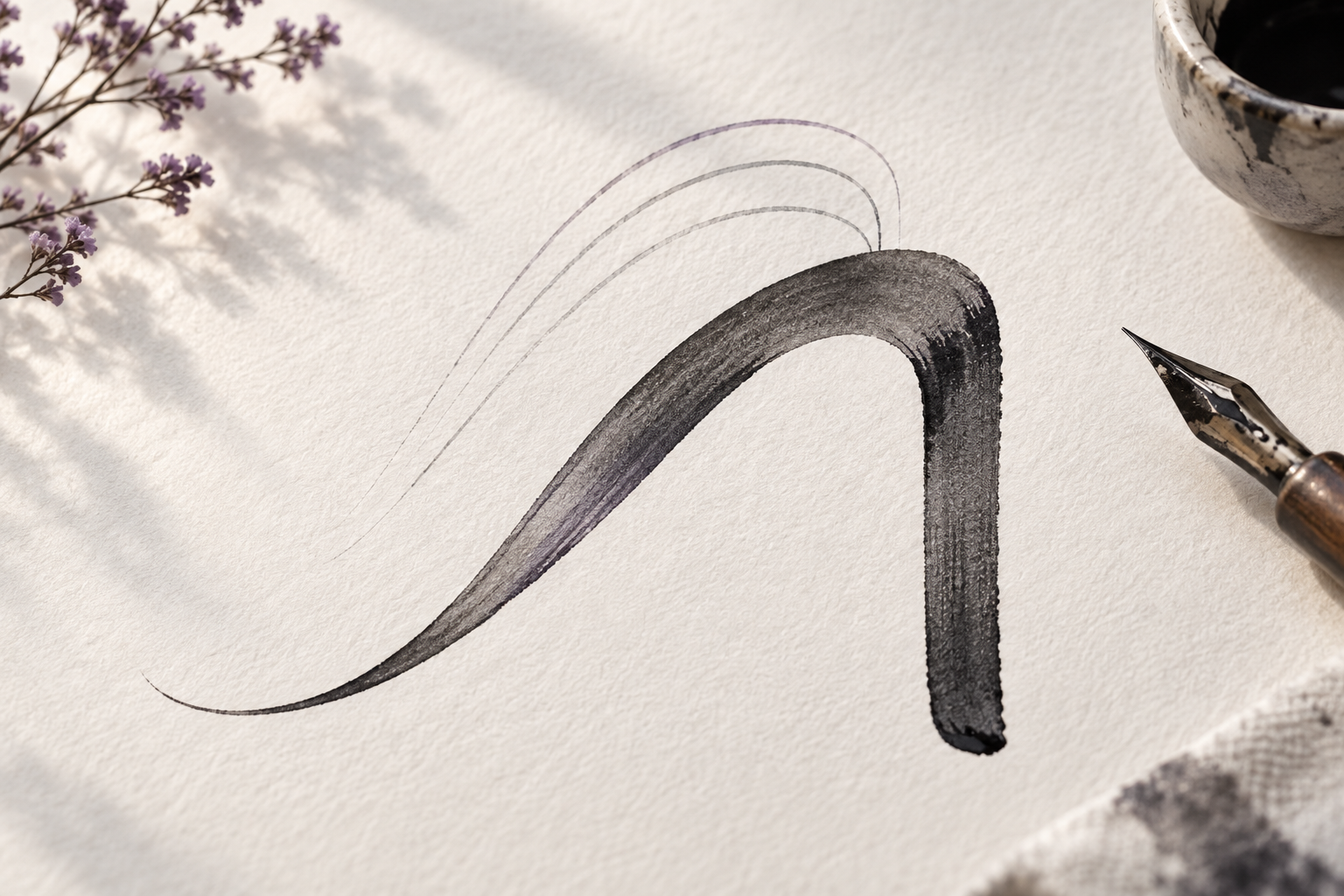
В строчной «ч» дуга должна перейти в правую стойку так, чтобы знак выглядел продолжением общего почерка, а не отдельной геометрической конструкцией. Начните с каркаса и точек перехода, затем настройте ширину чаши, наклон стойки и толщину на повороте. Такой порядок помогает избежать жёсткого угла, провисающей дуги и случайно тяжёлого правого края.
Что именно решает рисунок строчной «ч»
У этой буквы небольшой набор деталей, поэтому каждая заметна: левая сторона поднимается в дугу, дуга возвращается вниз и заканчивается правой стойкой. В рукописном начертании траектория зависит от того, как задуман жест: дуга может быть широкой и мягкой или компактной и энергичной, а стойка — почти вертикальной или слегка наклонённой. Важно, чтобы переход между ними был понятен и повторял логику остальных букв.
«Ч» часто кажется простой, пока её не ставят рядом с «и», «ш», «щ» и «п». Тогда обнаруживается, что чрезмерно округлая дуга сбивает темп, а слишком прямой верх превращает знак в чужую деталь. Стойка может начинаться слишком резко, перетягивать на себя взгляд или уходить в сторону. Эти эффекты не исправляются одинаковым наклоном всех штрихов: сначала нужно договориться о форме каркаса, затем настроить движение и только после этого добавлять характер пера.
Считайте каркасом основную траекторию знака — без утолщений, терминальных штрихов и декоративных выходов. Отметьте базовую линию, высоту строчной зоны, точку самого высокого участка и место, где дуга переходит в стойку. Эти ориентиры дают возможность сравнить несколько версий, не привязываясь сразу к обводке.
Выберите характер дуги до прорисовки контура
Сначала решите, какое ощущение должна создавать «ч» в вашем алфавите. Спокойная дуга может иметь плавный подъём и неглубокую вершину; более быстрая — выраженный угол поворота и заметный направленный выход. Угол не обязан быть математически круглым. Важнее, чтобы форма совпадала с жестом букв «и», «ш» или «л», если у них похожий переход от подъёма к спуску.
Нарисуйте три быстрых каркаса одинаковой общей высоты. В первом используйте широкую чашу, во втором — более тесную, в третьем — асимметричную: длинный подъём и короткий спуск. Не старайтесь выбрать победителя сразу. Поставьте варианты рядом с буквами из своего эскиза и посмотрите, какая дуга поддерживает темп, а какая создаёт чуждый акцент.
Ширина дуги влияет на боковой ритм строки. Широкая «ч» может быть выразительной в заголовочном шрифте, но в плотном тексте она будет оттеснять соседние знаки. Узкая форма экономит место, однако при чрезмерном сжатии теряет открытость и становится похожей на зажатую петлю. Сравнивайте ширину не только по внешнему контуру, но и по свободной области внутри чаши: именно её форма часто задаёт ощущение лёгкости.
Проверьте симметрию как вариант, а не как правило. Левая и правая части чаши могут отличаться по длине и наклону, если этого требует рукописный жест. Но если правая сторона уже отвечает за стойку и тянет вниз, её верхнюю часть не обязательно дополнительно утяжелять. Оставьте в эскизе несколько решений и отметьте, чем они отличаются: «вершина выше», «переход позже», «правая часть короче».
Как провести переход в правую стойку
Переход — ключевой участок буквы. Сначала определите его положение: дуга может заканчиваться близко к правому краю или продолжаться дальше, прежде чем начнётся стойка. Чем резче смена направления, тем заметнее будет характерный излом. Плавный переход смягчает знак, но может сделать верх слишком округлым и лишить его опоры.
Полезно отдельно нарисовать направляющую движения. Проведите карандашную линию от левого нижнего начала, вверх по дуге и вниз вдоль правой стороны. Остановитесь в точке смены направления и оцените касательную: продолжается ли там движение или траектория резко ломается? Даже если выбранный стиль намеренно угловатый, перелом должен выглядеть осмысленно и повторяться в других знаках.
Теперь проверьте длину правой стойки. Её вертикальная часть должна быть достаточно ясной, чтобы завершить знак, но не настолько длинной и тяжёлой, чтобы восприниматься как самостоятельная линия. Сравните её с близкими по наклону вертикалями в «и», «н» и «п». Не копируйте длину механически: ориентир нужен, чтобы заметить, когда «ч» вдруг выглядит намного вытянутее или массивнее.
Положение точки перехода можно сдвигать небольшими шагами. Если опустить её, дуга станет выше и более раскрытой; если поднять — чаша будет компактнее, а правая часть короче. Проверяйте оба результата в слове. Изолированная буква может казаться аккуратной, но в сочетании «чт», «ча» или «чи» поворот способен создать неожиданную пустоту или тяжёлое пятно.
Толщина на повороте и работа инструмента
Линии разной толщины — часть характера, но добавление ширины на повороте нужно контролировать. При работе ширококонечным пером направление инструмента меняет видимую насыщенность, а в монолинейном рисунке толщина может оставаться более ровной. В обоих случаях переход дуги в стойку способен визуально утолщиться: штрихи меняют направление, накладываются или проходят близко друг к другу.
Для начала нарисуйте «ч» одной простой линией, затем создайте её контур по правилам, которыми вы оформляете соседние буквы. Если весь шрифт строится как монолиния, не добавляйте локальный контраст только потому, что изгиб кажется скучным. Если у инструмента есть выраженное давление, сопоставьте изменение толщины с дугами «ш» и «л», а не придумывайте для «ч» отдельную систему.
На крупном эскизе отметьте места, где линии сближаются. Посмотрите на них в обычном размере и в уменьшенной копии. Если поворот превращается в тёмный узел, сначала разведите траектории или измените радиус изгиба. Затем проверьте натяжение линии: слишком длинный прямой участок прямо перед поворотом делает его тяжёлым, а слишком короткий может оставить стойку без ясного начала.
Если вы рисуете пером на бумаге, повторите дугу несколько раз без обводки. Сохраняйте одинаковыми размер и условия, но меняйте только скорость или давление. Если используется карандаш, маркер или цифровой планшет, сравните эскизы без автоматического сглаживания и с ним: сглаживание иногда стирает тот ритм, ради которого выбрана форма. На этом этапе задача не в точном копировании одной удачной линии, а в понимании устойчивого жеста.
Пошаговый способ построения
- **Задайте высоту и наклон.** Используйте те же ориентиры, что и для остальных строчных букв. Проверьте, не станет ли дуга заметно ниже или выше соседнего ряда.
- **Нарисуйте осевой жест.** Одной линией обозначьте подъём, вершину дуги, поворот и правую стойку. Пока не думайте о толщине.
- **Сравните ширину чаши.** Сделайте несколько версий с разной шириной и внутренним просветом. Оставьте те, которые вписываются в боковой ритм выбранного алфавита.
- **Проверьте точку смены направления.** Сдвигайте её на небольшое расстояние вверх и вниз. После каждого изменения записывайте, что стало лучше или хуже.
- **Постройте контур.** Примените характер штриха и способ окончания, уже выбранные для других знаков. Проверьте темные участки на повороте.
- **Соберите короткие слова.** Возьмите сочетания с разными соседями: «чаша», «чуть», «точка», «свеча». Меняйте только один параметр за раз.
- **Уменьшите пробу.** Смотрите на строку в реальном предполагаемом размере. Если дуга схлопывается или стойка исчезает, вернитесь к каркасу.
Храните рядом две-три версии, а не только финальную. Между ними должно быть легко увидеть, что изменилось: ширина, глубина дуги, положение вершины или длина стойки. Когда несколько параметров меняются одновременно, становится трудно понять, почему одна буква работает лучше другой.
Сверка с остальным алфавитом
Поместите «ч» в ряд с «и», «ш», «щ» и «п», если они уже готовы. Сравнивайте только один признак за проход: округлость вершин, высоту, наклон или общий вес. Так вы увидите, где буква повторяет полезную закономерность, а где копирует её слишком буквально. Удачная согласованность не означает, что каждый изгиб должен быть одинаковым.
Затем вставьте знак в короткую строку из слов, где он стоит в начале, середине и ближе к концу. Посмотрите на пространство по обе стороны: не заставляет ли широкая дуга раздвигать весь набор? Не упирается ли стойка в штрих соседней буквы? Сначала оцените визуальную паузу в паре, затем темп всей строки. Боковые поля можно корректировать после рисунка контура, но они не должны маскировать принципиально неудачную ширину.
Сделайте контрольную пробу на белом фоне и на рабочем фоне, если буквы будут использоваться в цветном макете. Контраст окружения меняет субъективную толщину штриха, поэтому форма, которая кажется лёгкой на белом, может стать слишком плотной на насыщенном цвете. Не пытайтесь лечить фон изменением одного знака, пока не проверили остальной шрифт в тех же условиях.
Перенос рисунка в векторный контур
Когда эскиз выбран, не обводите каждую неровность буквально. Сначала поставьте узлы в местах изменения направления: у основания подъёма, на вершине дуги, в точке перехода и у нижнего конца стойки. Между ними оставьте кривым описывать плавные участки. Если узлов много и они расставлены через равные интервалы, контур часто начинает дрожать, хотя исходный жест был уверенным.
Сохраните рядом исходный рисунок и первую цифровую версию. Наложите их друг на друга и проверьте три места: не сместилась ли вершина, не стал ли переход угловатым, не укоротилась ли стойка. Затем посмотрите на контур без эскиза: цифровая буква должна выглядеть цельно, а не зависеть от направляющей. При необходимости поправляйте ручки узлов малыми движениями и после каждого изменения сравнивайте пару буквенных размеров.
Если строчная «ч» должна соединяться с соседями, проверьте направление начала и окончания формы до экспорта. Точка, удобная для редактирования, может оказаться неудобной для соединения в слове. Лучше оставить простой запасной вариант каркаса, чем заставлять контур поддерживать один фиксированный выход. Так основная форма останется стабильной, а связность можно будет настраивать отдельно.
Типичные ошибки
- **Делать вершину идеальной аркой.** Геометрически гладкая дуга иногда выглядит чужой среди живых штрихов. Сверьте её с формой соседних букв и верните нужное напряжение линии.
- **Уводить стойку слишком сильно вправо.** Внешний край становится тяжёлым, а буква раздвигает соседей. Сначала поправьте точку перехода, а затем оценивайте поля.
- **Ломать дугу ровно в месте стойки.** Если переход выглядит случайной ступенькой, попробуйте изменить радиус и направление входа. Намеренная угловатость тоже должна поддерживать общий почерк.
- **Сразу добавлять толстый контур.** Обводка отвлекает от ошибки каркаса. Проверьте основную линию и просвет до работы с толщиной.
- **Оценивать только отдельно.** В строке становятся заметны паузы, слипание и разница веса. Смотрите на букву и в словах, и в ряду похожих форм.
- **Менять много параметров одновременно.** При такой правке невозможно связать результат с конкретным решением. Делайте небольшие сравнимые итерации.
Контрольный список
- Понятна ли основная траектория от левой стороны дуги к правой стойке?
- Согласованы ли высота и наклон с другими строчными буквами?
- Не выглядит ли чаша излишне широкой, тесной или низкой рядом с «и», «ш» и «п»?
- Выглядит ли поворот намеренным, а не случайной ступенькой?
- Не утолщается ли место соединения после добавления контура?
- Сохраняются ли характер дуги и стойки при уменьшении?
- Проверена ли форма в нескольких словах и на строке?
### Обязательно ли делать правую стойку почти вертикальной?
Нет, её наклон зависит от общей пластики шрифта. Сравните стойку с другими близкими по направлению штрихами. Она должна выглядеть родственницей, сохраняя при этом собственный переход из дуги.
### Как выбрать ширину дуги?
Сделайте несколько каркасов одной высоты с разной шириной, затем посмотрите на внутренний просвет и боковые интервалы в словах. Ширина должна соответствовать характеру гарнитуры и не ломать темп строки.
### Нужно ли рисовать «ч» одним движением?
Это полезный способ найти естественный жест, но финальный знак можно строить из отдельных контуров. Даже при раздельном построении проверяйте, ощущается ли непрерывность и согласуется ли она с тем, как нарисованы другие буквы.
### Как исправить резкий угол на вершине?
Сначала измените направления входящего и выходящего штрихов, а не только сглаживайте узел. Попробуйте немного сдвинуть место перехода и сравните версии в строке, чтобы не потерять характер знака.
### Почему буква выглядит тяжелее после векторизации?
Контурные линии могут наложиться или сблизиться у поворота, а сглаживание — изменить исходную траекторию. Сравните вектор с эскизом при одинаковом размере, разведите контуры и удалите лишние узлы, не меняя выбранную конструкцию.
### Как понять, что форма готова?
Когда её основные решения — ширина, высота, поворот и наклон — стабильно работают отдельно и в словах. Если знак каждый раз требует нового исправления при смене окружения, вернитесь к каркасу и проверьте, не противоречат ли друг другу его части.
Строчная «ч» держится на согласованном движении от дуги к правой стойке. Начните с простого каркаса, сравните ширину и точку перехода, затем добавьте характер штриха и проверьте форму в словах и малом размере. Так вы сохраните индивидуальность знака без разрыва с общим стилем.